چگونگی ضخامت حروف فارسی و عربی
چرا شیوهی بهکارگیری ضخامت در حروف فارسی و لاتین متفاوت از یکدیگرند؟
قلمهای خوشنویســی در خط فارســی/ عربی از نظر اندازه و شکل با قلمهای خوشنویسی لاتین متفاوت است و قط قلم با شیب و زاویه بیشــتری برش میخورد و راستای نوشتن با قلم برعکس راستای لاتین و از راست به چپ است. این ویژگیها سبب شکلگیری سبکی متفاوت در خط فارســی/ عربی نسبت به خط لاتین شد. بر این اساس حروف فارســی/ عربی دارای حرکات افقی ضخیم و حرکات عمودی نازک هستند. کاربرد پهنا و نازکی در خوشنویسی فارســی/ عربی قوت و ضعف خوانده میشود. قوت، بخش قویتر حروف است و ضعف قسمتهای نازک حروف را شامل میشود. به عنوان مثال مواصلات و قسمت پایین دوایر نون و سین و… بیشترین پهنای خط را داراست و ضعفها اغلب در گردشهای قلم و دنباله های حروف نمایان است. قوت معمولاً با بهرهگیری از تمام دَم قلم بر سطح کاغذ و ضعف با به کار بردن جزئی از دَم قلم و نیش قلم حاصل میگردد.
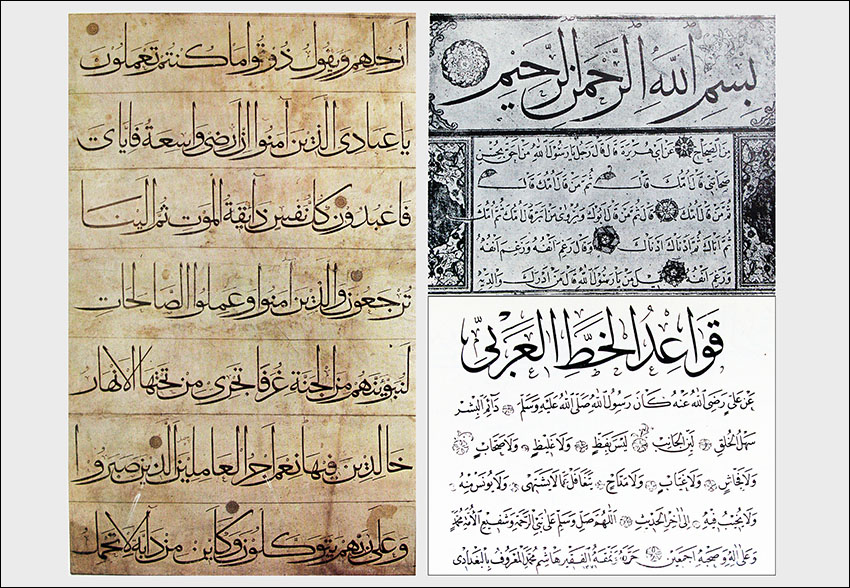
در کتابت خط لاتین، دَم قلم دارای برش عمودی بود و قلم از چپ به راست و با زاویۀ روی کاغذ قرار میگرفت. زاویۀ برش قلم و شکل قرارگیری قلم بر ســطح کاغذ، سبب شکلگیری حرکات عمودی ضخیم و حرکات افقی نازک میشد. در برخی از خطوط لاتین، خطوط افقی نازک برای اتصال حروف به یکدیگر به کار میرفت.
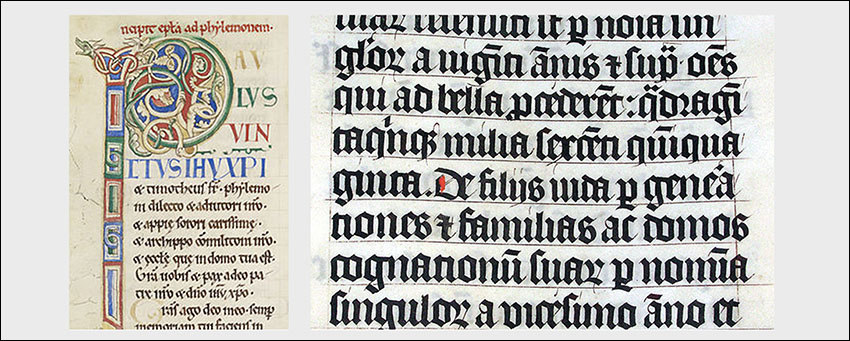
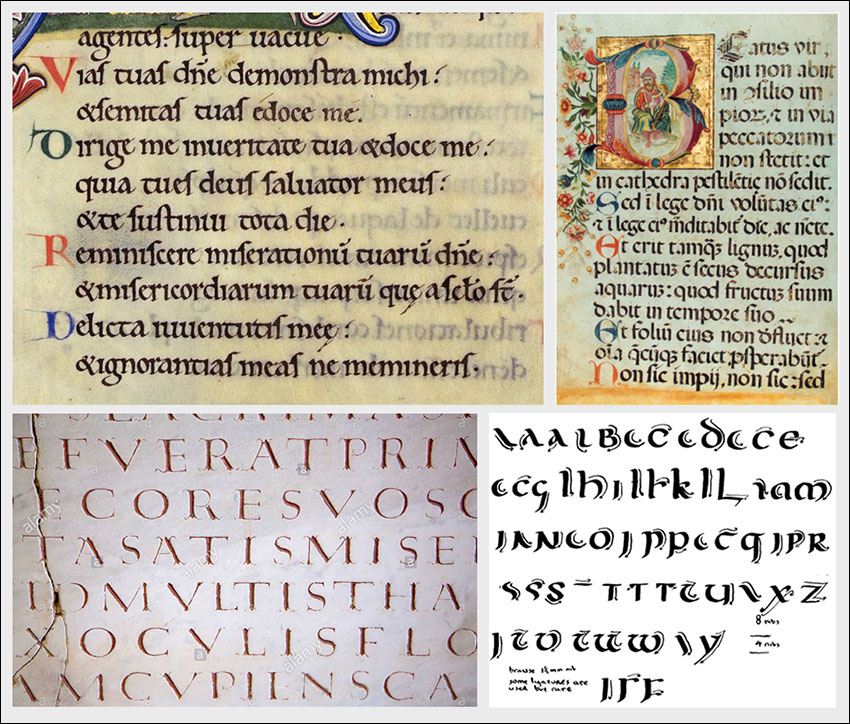
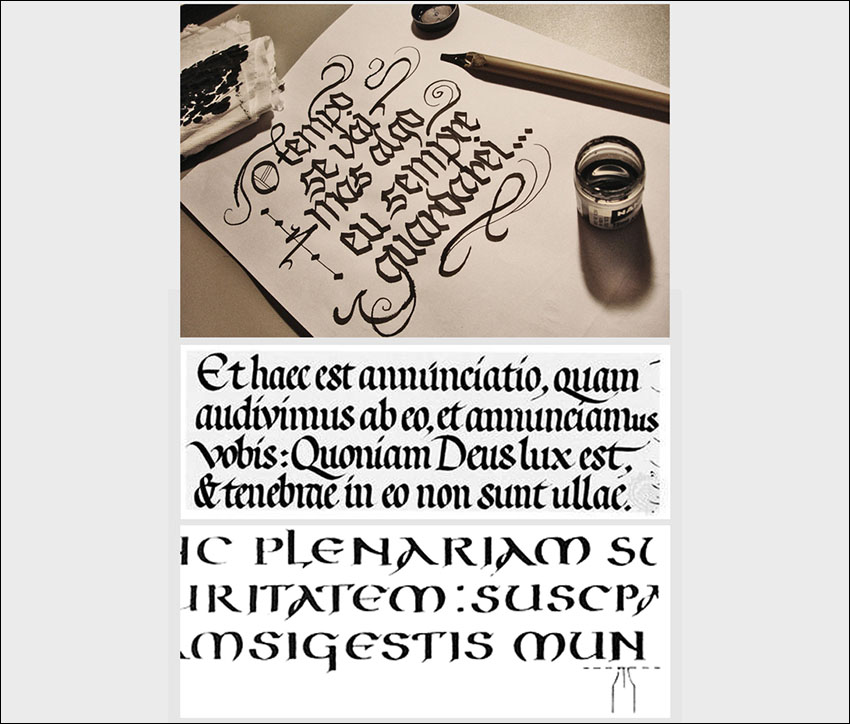
در خط فارســی/ عربی اغلب قوت در حرکات افقی و ضعف در حرکات عمودی و گردشهای قلم به کار رفته با این حال طی مطالعات انجام شده مشخص شد که گاه در برخی از خطوط مانند کوفی شرقی و برخی از نمونههای خط کوفی اولیه گاه شاهد تغییر در شیوه به کارگیری قوت و ضعف هستیم، به نظر میرسد این ویژگی به خاطر نوع برش قلم و شیوه قلمرانی باشد. خصوصیتی که تا به حال کمتر به آن توجه شده و میتواند زمینه تحقیق و توجه پژوهشگران و طراحان حروف را فراهم کند. نکته جالب توجه این است که همانند اتصالات خط لاتین که به شکل نازک به کار میرفت، در برخی از نمونههای کوفی شرقی۱ گاه اتصالات نازک دیده میشود.
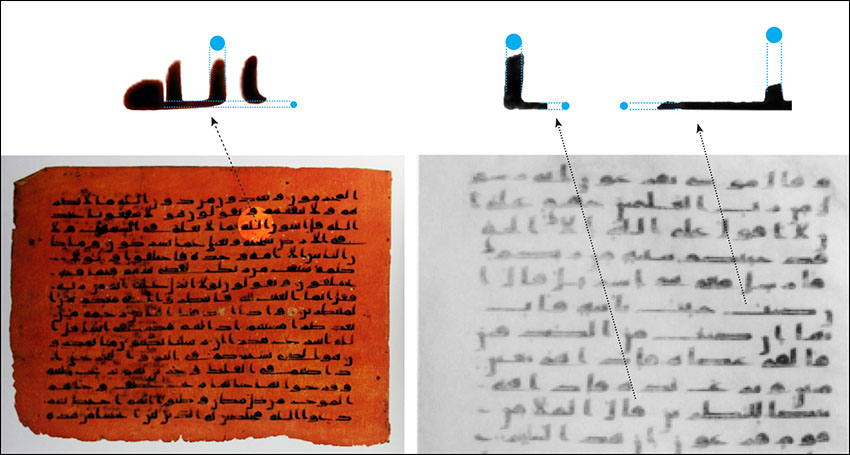
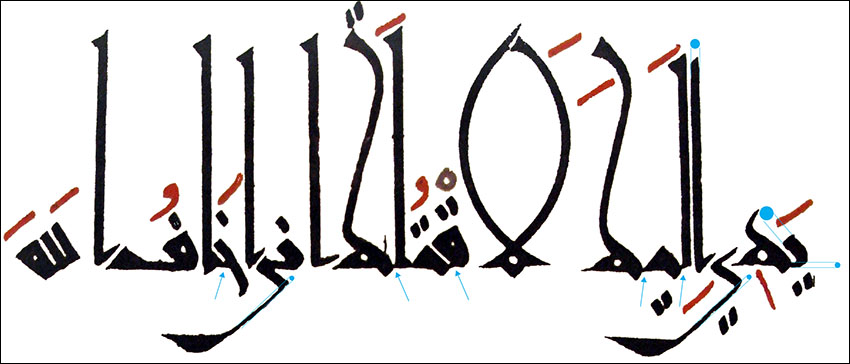
۱. در کوفی شرقی حروف منفصل و متصل در ابتدا به صورت جدا از هم نوشته میشد و سپس حروف متصل با خطی موئین به هم اتصال مییافت.